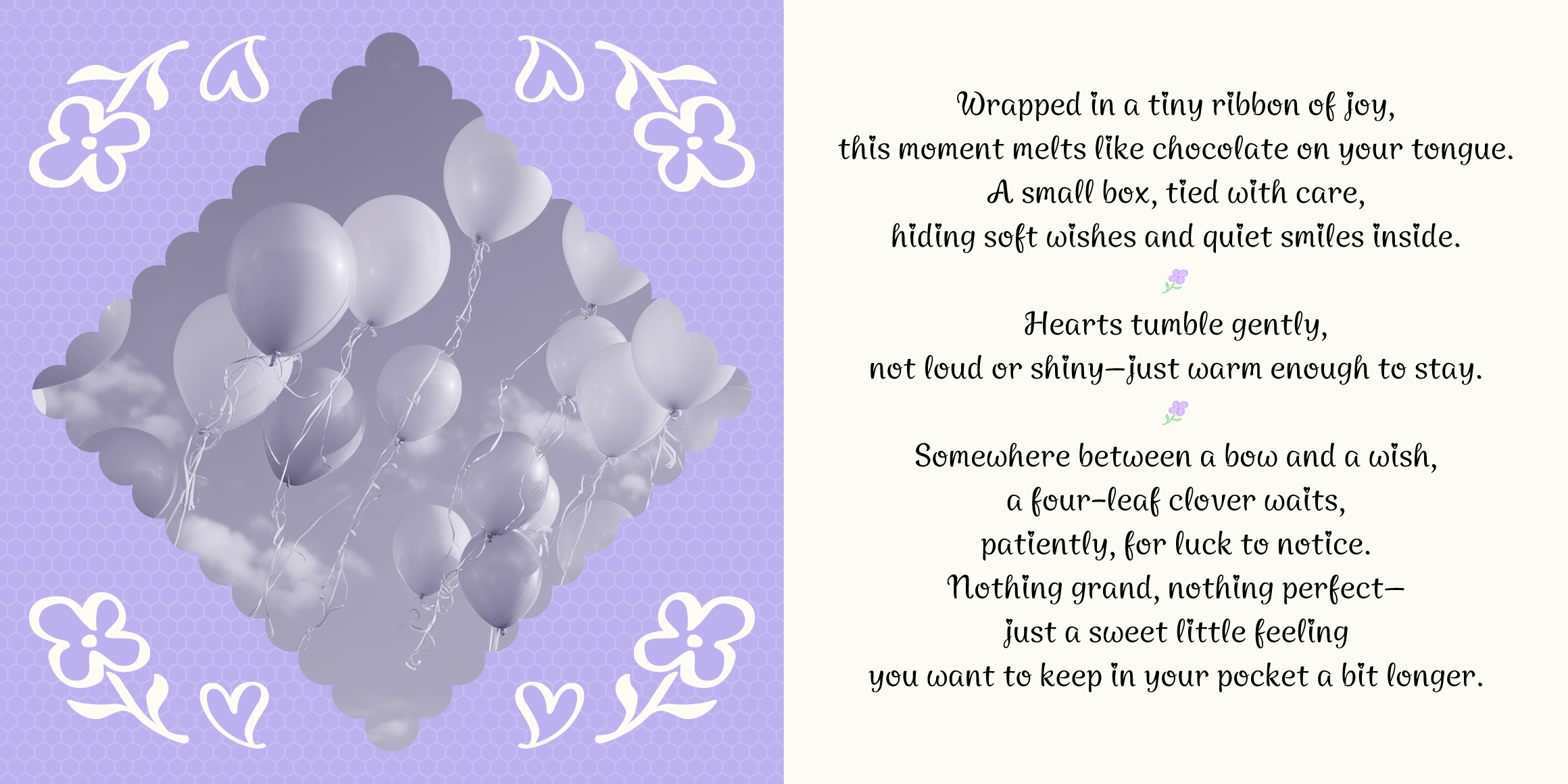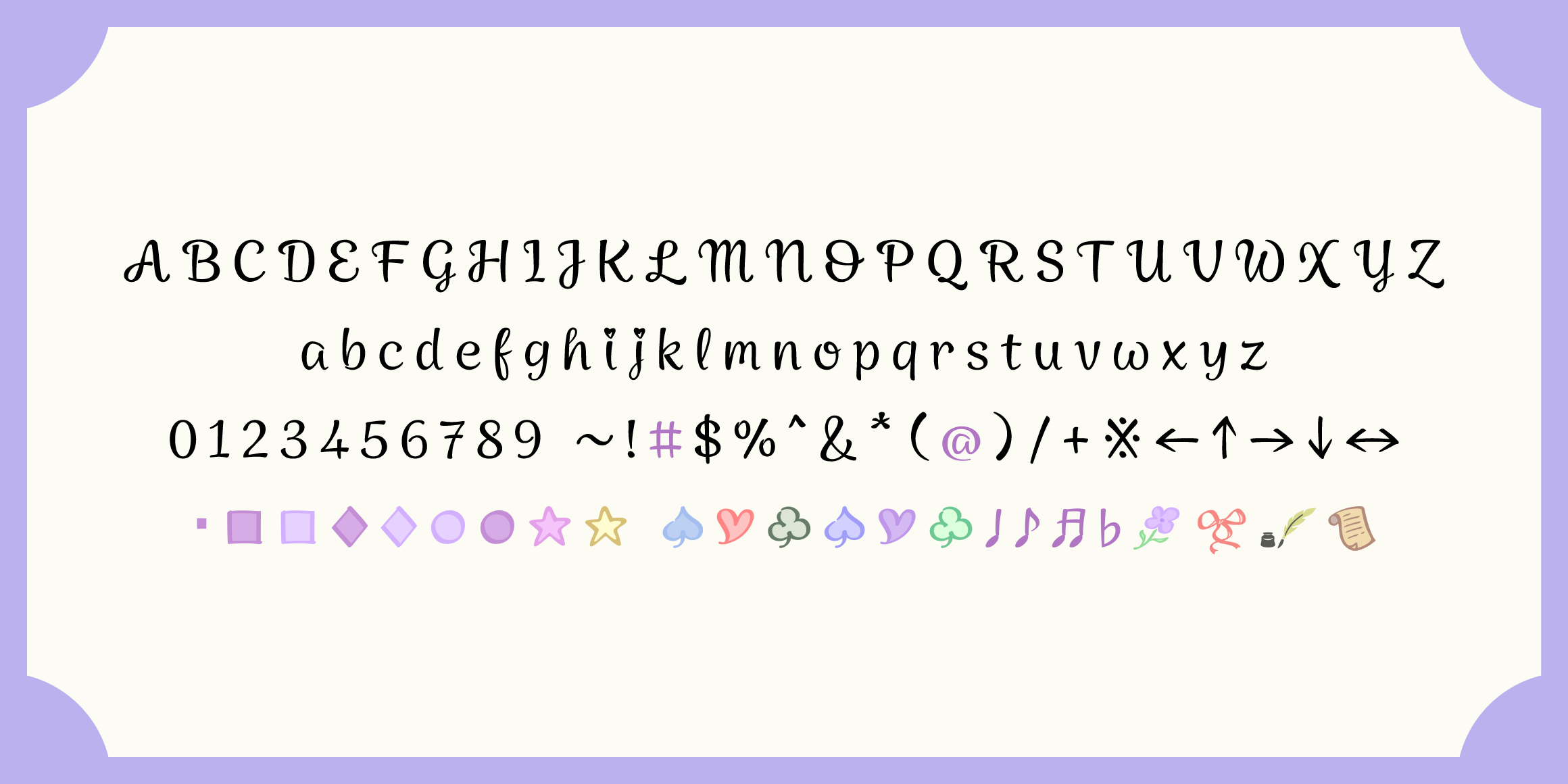
i와 j의 점(dot)은 작은 하트 모양으로 디자인되어 사랑스럽고 달콤한 매력을 더해줍니다.
넉넉한 크기의 소문자를 사용하여 뛰어난 가독성을 제공하면서도, 장난스럽고 개성 있는 분위기를 유지합니다.
감성적인 손글씨 스타일은 정성껏 쓴 편지 같은 따뜻함과 개성을 느끼게 해줍니다.
또한 이 폰트에는 꽃, 리본, 깃펜, 편지지 등 4가지 테마의 딩뱃(Dingbat)이 포함되어 있어, 부드럽고 로맨틱한 콘셉트와 완벽하게 어우러집니다.
JjDearLilac과 함께, 마치 진심을 담은 편지를 쓰는 듯한 소박한 즐거움을 경험해 보세요.
;), ;>, :!:, :?: 를 입력하면 숨겨진 딩뱃이 나타납니다!
# @ ■ □ ▪ ◆ ◇ ○ ● ★ ☆ ♠ ♡ ♣ ♤ ♥ ♧ ♩ ♪ ♫ ♬ ♭ 문자에 컬러 딩뱃을 지원합니다.
컬러 딩뱃을 지원하지 않는 환경에서는 흑백으로 표시됩니다.